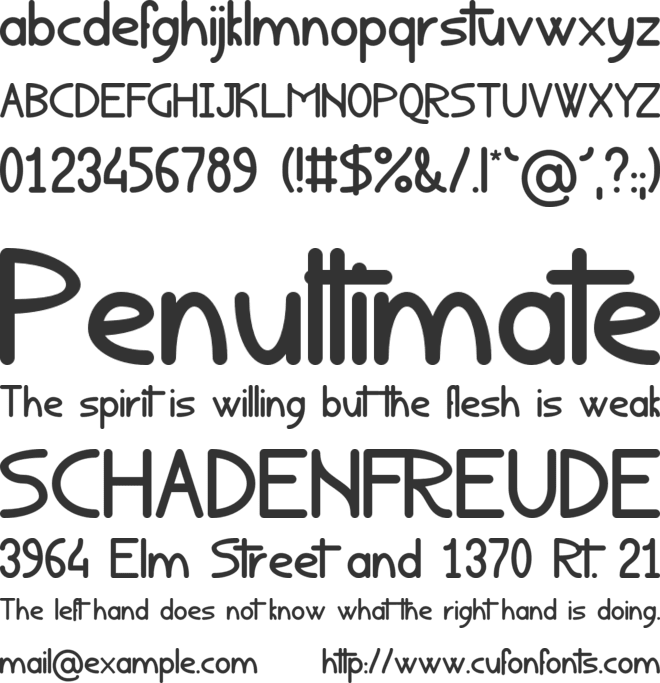
Rondouillard Font Family
J'ai créé Rondouillard en 3 semaines, du 9 octobre au 2 novembre 2013. Le style me plaît, l'alignement des caractères me semble plus réussi que pour Micursif. Je l'ai créé avec FontForge, logiciel que je recommande aux utilisateurs de Linux (il ne fonctionne pas sous Windows). Police toujours aussi complète que mes précédentes, Rondouillard contient le latin de base (notre alphabet), les latins étendus (Latin-1 [accents], Latin étendu A, Latin étendu B, Latin étendu C, Latin étendu additionnel), l'alphabet grec et le grec étendu, l'alphabet cyrillique de base, l'alphabet phonétique (Ext. IPA, Alph. phon. International, Alph. phon. étendu), les fractions, exposants et indices, signe Euro, ponctuation, nombres entourés de 0 à 50 et autres Alphanumériques joints, symboles du jeu du pendu, dominos, cartes à jouer, etc, soit en tout 3036 caractères. De plus, elle est faite en 4 versions (Normal, Gras, Italique et Gras-Italique). Correctement installées, ces versions ne forment qu'une police qui, quand on la met en Gras ou en Italique, utilise les autres versions. J'ai réussi sur Ubuntu (il suffit d'installer les 4 une par une) mais pas sur Windows. Si vous trouvez une solution, merci de m'en parler par mail.